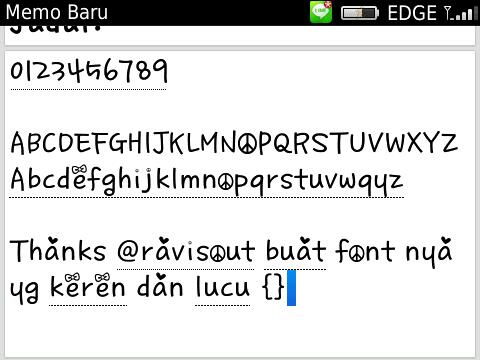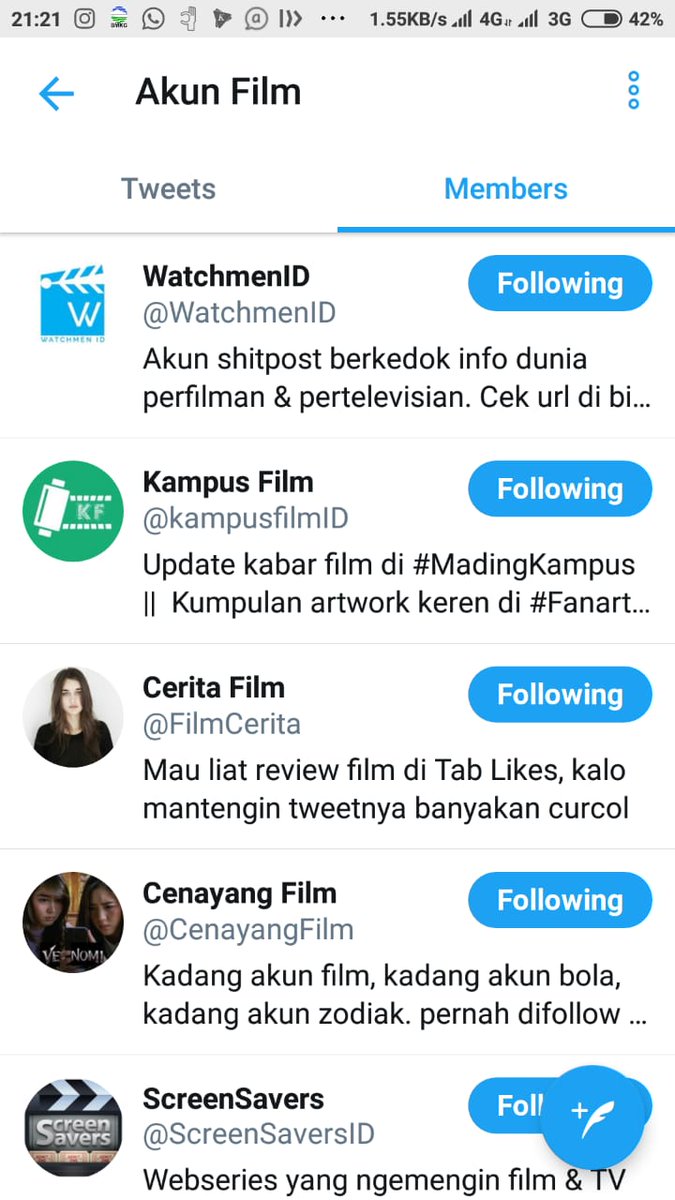
28+ Font Keren Twitter Images. They just know a few little unicode secrets that allow them to seemingly make their tweet font bold, italic. Font keren ✅ (cσρყ αɳԃ pαʂƚ).
What Font Does Twitter Use Quora from qph.fs.quoracdn.net Twitter changed its primary font on friday, moving to a sleeker and narrower look. Each letter will be converted into. Sebagai seorang designer, tipografi adalah hal yang sangat penting.
Urban fonts adalah website penyedia font keren gratis lainnya yang bisa jadi pilihan. Di era modern seperti sekarang ini, produk digital menjadi aset penting dalam hidup seseorang. Urban fonts adalah website penyedia font keren gratis lainnya yang bisa jadi pilihan. The font change appears across the twitter.com site, on user profiles and sidebars, and on tweets and individual.